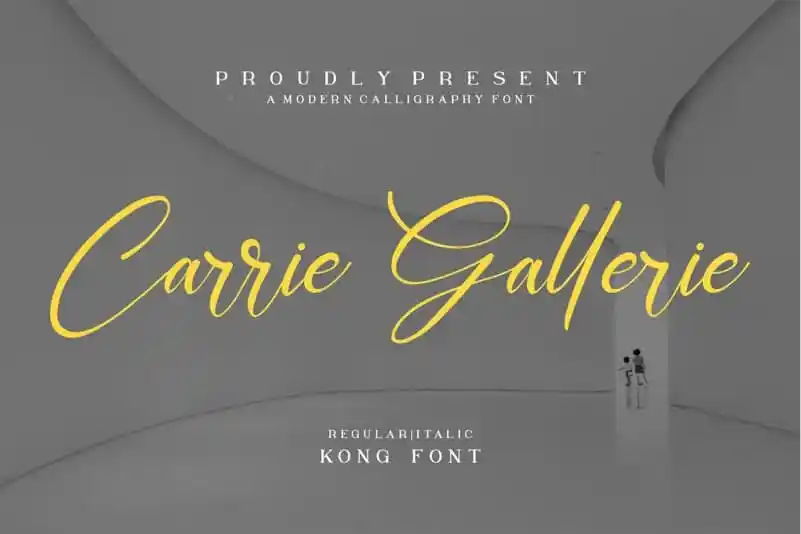
Carrie Gallerie Calligraphy Font é uma elegante fonte script que carrega consigo uma sensação natural e suave. Seu design fluido e delicado cria um toque suave e atraente para qualquer projeto de design, especialmente quando usada em cartões de convite, logotipos, capas de livros ou até mesmo em trabalhos manuais. Com seus detalhes cuidadosamente elaborados e suas linhas levemente onduladas, essa fonte irá adicionar um toque natural a qualquer projeto, garantindo que todas as informações exibidas sejam apresentadas com delicadeza e beleza. Adaptada para uma variedade de usos, é perfeita para projetos de design diversos, tornando-a um recurso valioso para designers gráficos do mundo todo.